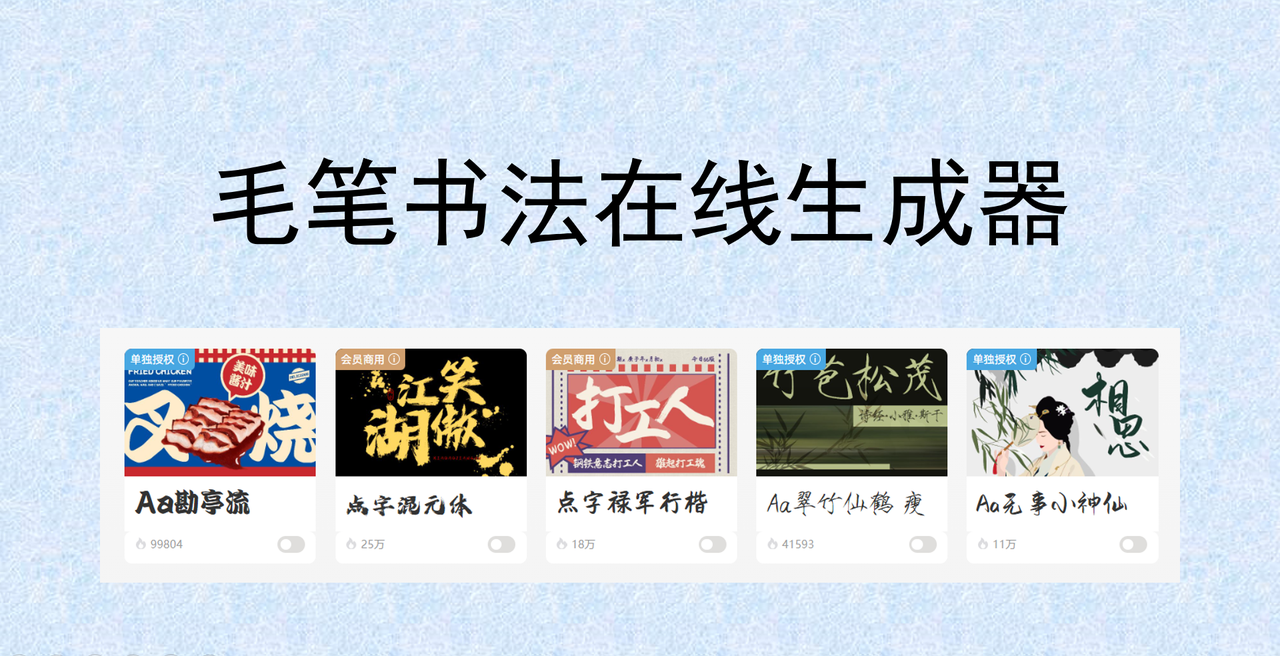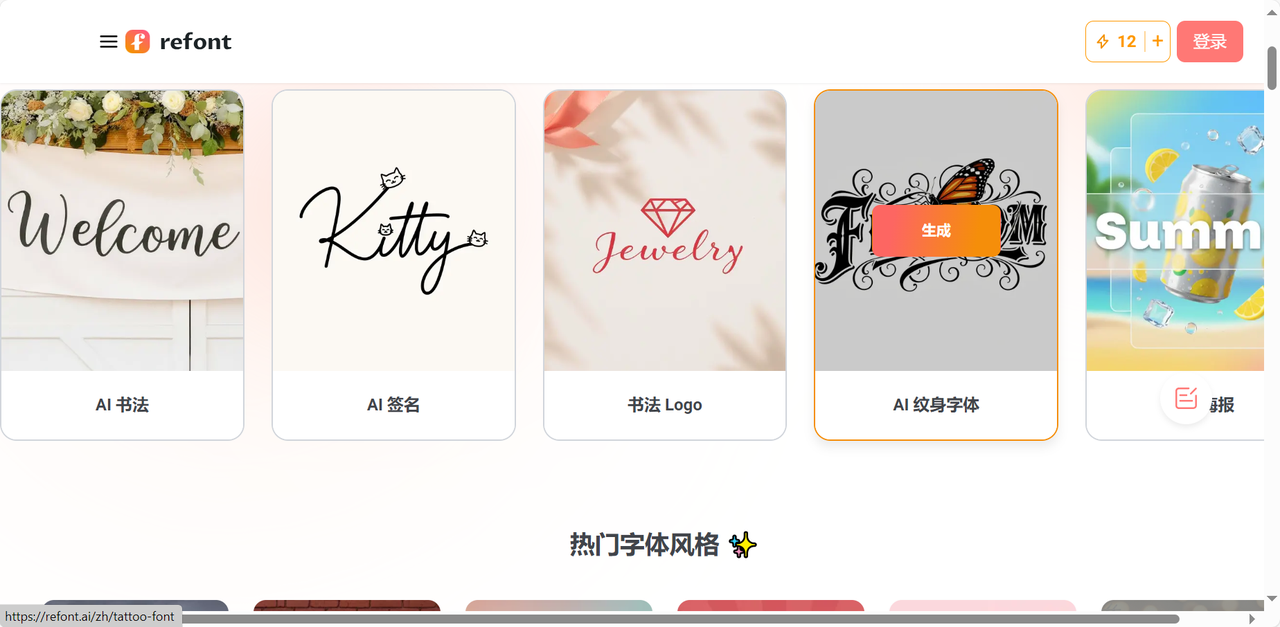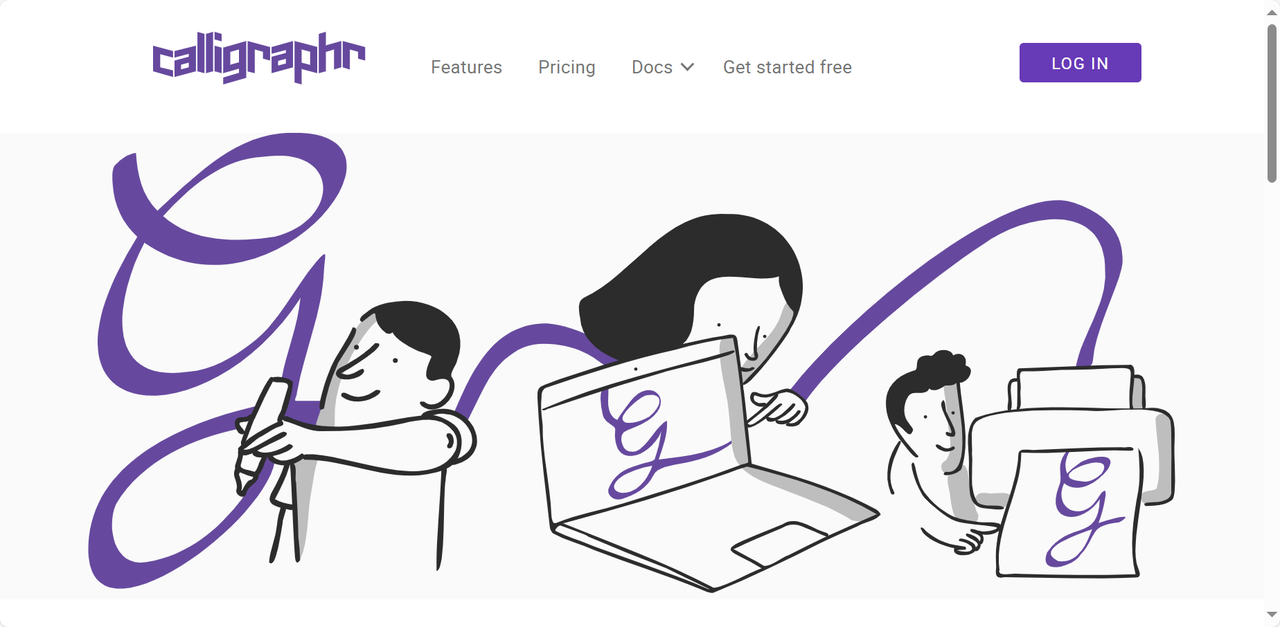
毛笔书法在线生成器,输入文字秒变书法大家
是不是经常在做设计的时候发现缺了一点笔墨韵味?那是因为没有选择书法字体!好看的毛笔书法字既能提升作品的质感,又可以传递文化古韵。不用自己学习如何书写毛笔字,也不需要学习复杂的 PS 来调整笔墨色彩,只需要找到一个好用的毛笔书法在线生成器就能搞定一切。今天就给大家推荐 4 款毛笔书法字在线生成器,输入文字就能一键生成堪比书法大家的作品,瞬间拥有专业级的书法特效。这些工具的免费版就可以满足大多数设计项目的需要,轻松获得书法字体,再也不用羡慕别人的一手好字了!
一、字由
字由是目前国内设计师用的最多的字体管理与 AI 工具平台,注册用户远超 2000万,它不仅提供了大量正版可商用的书法字体资源,而且内置的 AI 字体功能更是“输入文字秒变书法”的神器。着重来讲一下字由的 AI 字体功能吧,操作非常简单,三步就可以生成一个专业的书法字体图。用户在 AI 字体页面内选择一个自己喜欢的模板,可以按照“书法风”进行筛选,点击“做同款”,在文字编辑区域输入你想生成的文字内容,点击“立即生成”,等待 10 秒左右就可以获得一张高清的毛笔书法字体。这里需要注意一下,最好和模板原本的字数保持一致,生成效果会更加自然。生成后的图片可以直接下载成透明背景的 PNG 图片,直接拖进其他设计软件内使用,没有水印且分辨率高。在收费方面也非常友好,每天登录官网可以免费领取算力点,日常生成书法字的需求完全够用,无需额外花钱。字由在众多字体工具里,绝对是能一站式搞定字体设计的必备选择。
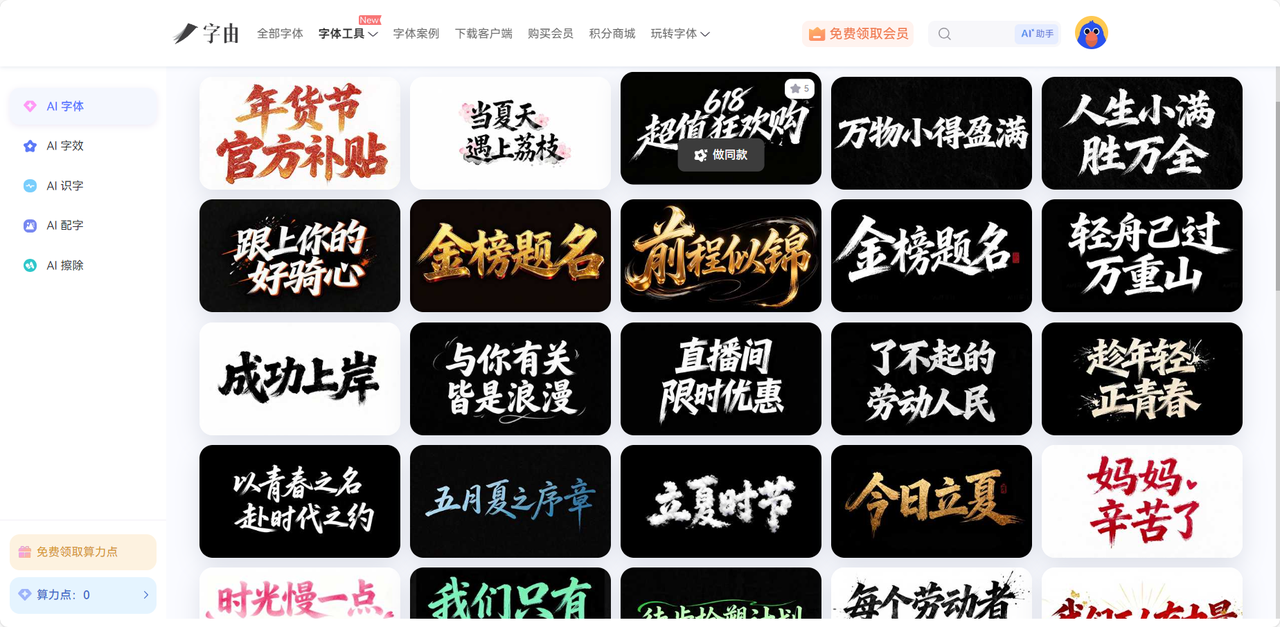
二、Refont AI
Refont AI 是一款基于人工智能等在线字体生成平台,仅需几秒钟就能直接生成多种精美的字体风格,比如书法字体、手写字体、签名字体、花式字体等,甚至也能直接生成书法风格的品牌 logo。最值得一提的就是 Refont A 的 AI 书法生成器功能,支持隶书、草书、楷书等书法风格不说,还能参考历史上著名书法家的笔触,生成更具有文化底蕴和书法家气质的同款字体。用户在输入框写下想要转换的文字,中文、英文或者短句都可以,这方面没有过多限制;然后选择你想要的书法类型,点击生成按钮,马上就能出现字体预览效果,不满意可以反复切换其他风格再次生成哈,直到获得你想要的毛笔书法字体。另外,Refont AI 还可以在生成书法字体之后添加背景纸(复古信纸、普通白纸、横线作业纸等),这样导出的字体自带纸张纹理,视觉效果更加自然真实。
Refont AI 还有一个我比较喜欢的功能,就是书法 logo 生成器,对于初创品牌工作室来说这真的是一个不可多得的宝藏工具。用户只需要输入品牌名称,系统会自动生成多个带有书法美感的 logo 供你挑选,且完全免费,生成的图片还支持商用哦。
三、Calligraphr
和上面两个书法字生成的逻辑不同,Calligraphr 是让你亲手创造属于自己的字体,也更佳考验用户的动手能力。Calligraphr 是一款来自加拿大的在线字体生成工具,可以直接将你的手写字体转化为专属的电子字体文件,然后安装到电脑上使用。如果你想要拥有一套独一无二只属于自己的书法字体,且你有一定的书法功底,那么这个工具就是你的最佳选择!我特地找了会书法的朋友来尝试,Calligraphr 具体的操作流程是这样的:登录官网之后下载对应的模板,自行打印出来后在模板内的对应区域用黑色签字笔填写英文字母、数字、标点符号,如果觉得打印很麻烦,也可以直接在纸上用毛笔书写一套文字;然后把自己写好的东西拍照上传到官网;等待系统自动生成即可。Calligraphr 会自动检测你书写的每一个字符的轮廓,并转换成电子字体,最终可以导出为一个完整的 TrueType 或 OpenType 字体文件,可以直接安装到你的电脑系统里哦,之后在各种设计软件中都可以随时取用。
最关键的是,Calligraphr 有一个字符随机化的功能,它支持你对同一个字符设置很多个变体,这样下次生成对应效果的书法字体时,系统会随机调用,模拟真实手写的自然差异,毕竟我们也不可能每次写字都一个样。我一直觉得这个功能非常有助于书法字体这种风格,因为会带有一定的手写温度和真实感,更容易拉近设计者和用户之间的距离。
四、Free Online Signature Generator BY FDM AI
最后一个要推荐的就是 Free Online Signature Generator BY FDM AI(以下简称为 FDM Tools),严格意义上来说,这是一个在线电子签名生成工具,最大的优势就是字体效果逼真,可以模拟真实自然的墨迹变化,很像手写出来的字体。和其他工具的不同的是,该工具完美保证了用户的隐私安全,所有书写和生成的过程都是在你的本地浏览器内完成的,不会上传到任何外部服务器,刷新页面后就会自动清除数据记录,很适合有商业保密需求的设计师们。与 Calligraph 类似,这款工具也需要你自己来写,用户在选择好字体风格后,需要用鼠标、触控板等工具在画板上书写想要的文字内容,FDM Tools 会实时捕捉你的书写速度以及线条粗细变化,最后生成一款符合你本人书写习惯的毛笔书法字。成品达到你满意的效果之后,可以直接导出为 PNG 格式的图片。就我个人观感来讲,FDM Tools 生成的书法字质感很真实,完全不输专业的书法作品,追求真实手写感字体的小伙伴,不妨来试一试。
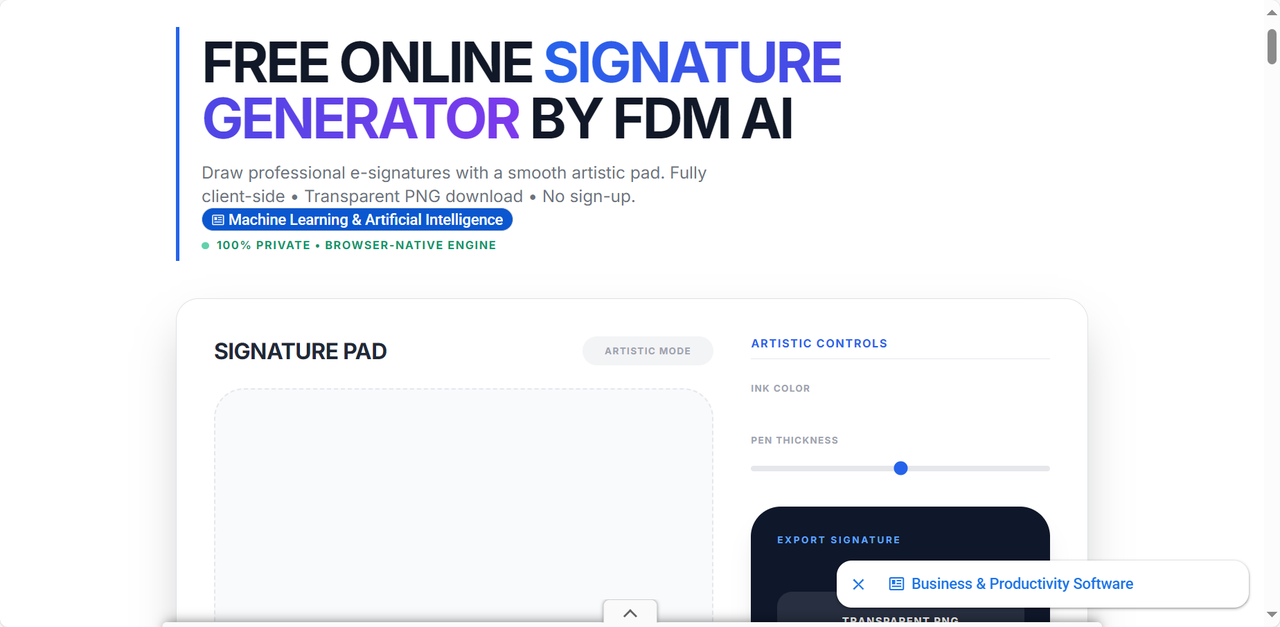
以上就是给大家推荐的 4 款毛笔书法在线生成器,输入文字就能体验一把书法大家的快乐。字由以 AI 工具一键生成同款书法字而被大家喜爱,更有上千款书法字体模板一键激活使用,对于国内设计师来说是绝佳选择;Refont AI 支持基础的书法风格,还能生成品牌 logo;Calligraphr 能把手写毛笔字转换为可在电脑上安装使用的专属字体;FDM Tools 则可以生成更加有真实感的字体。有了这些工具的帮忙,相信你一定能让你拥有自己满意的书法字体,普通文字秒变书法字!让你的作品更具质感和格调!